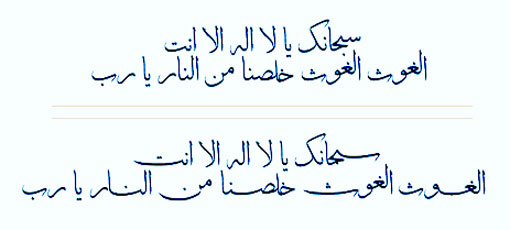
خط زیبای ثلث
توضیحات مهم: این فونت براساس فونت ثلث نرم افزار میرعماد ساخته شده است و با فونت ثلث های سابق تفاوت دارد. از تفاوت های ویژه این فونت میتوان به قابلیت کشیدگی اکثر حروف (با استفاده از SHIFT+J) اشاره کرد. و در نرم افزارهای تایپ پیشفرض ویندوز (NOTEPAD ,WORDPAD) و مایکروسافت آفیس به خوبی عمل میکند ولی در نرم افزارهای گرافیکی فتوشاپ، کرل، ایندیزاین و... عمل نمی کند. برای استفاده در فتوشاپ میتوانید متن تایپ شده را در نرم افزار ورد به فایل پیدیاف تبدیل کرده و آن را به محیط گرافیکی مورد نظر انتقال دهید. توجه داشته باشید خط ثلث در ایران برای نوشتن عنوان سورههای قرآن کریم، پشت جلدنویسی، سرلوحهها، و بخصوص در کتیبهها و کاشیکاریها بکار رفته و استفاده از آن هنوز نیز رایج است.